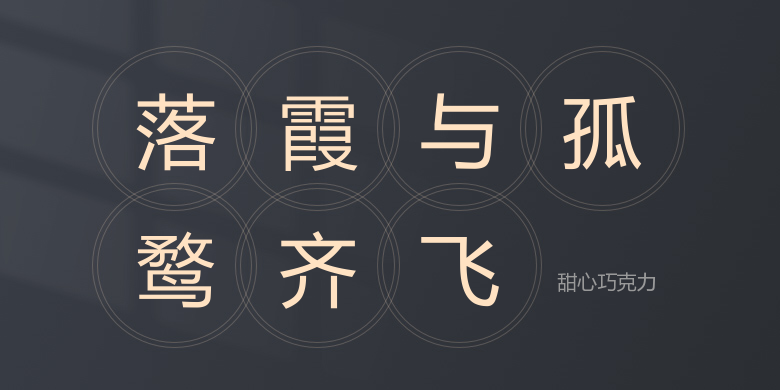
甜心巧克力
甜心巧克力,这款字体结构工整、笔画清晰,兼顾美观与易读性,适用于标题、正文、海报、包装、LOGO 等多种场景。字形优雅稳定,风格百搭耐看,适配日常排版与创意设计,让文字呈现更舒适、更具质感。甜心巧克力一笔一画,皆是细节,以均衡的比例、流畅的线条打造舒适视觉体验,字形端正大气,风格简约现代。无论是商业设计、品牌宣传还是日常排版,都能轻松驾驭,让文字更有格调与力量。甜心巧克力字体下载。